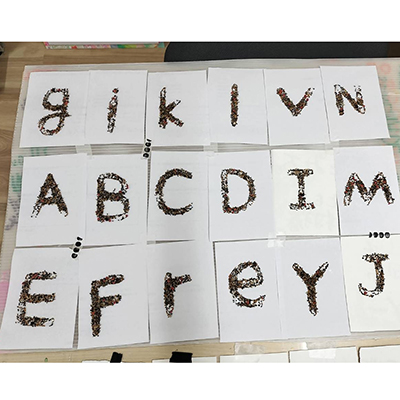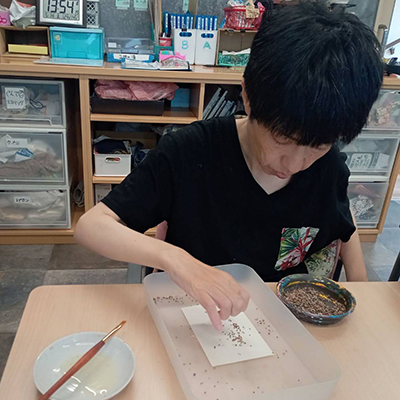
つぶパラフォント
種のつぶつぶそのまま文字に。
水耕栽培で採れたもう植えても芽が生えてこない種を使って制作した。(Sana)
デザイナーが糊で文字の形を書き、その上にアーティストがパラパラと種を撒いて作りました。息の合った連携作業で完成したフォントです。施設で行っている水耕栽培で不用になった種を使っており、施設らしいストーリーも込められています。(くるるえびす)